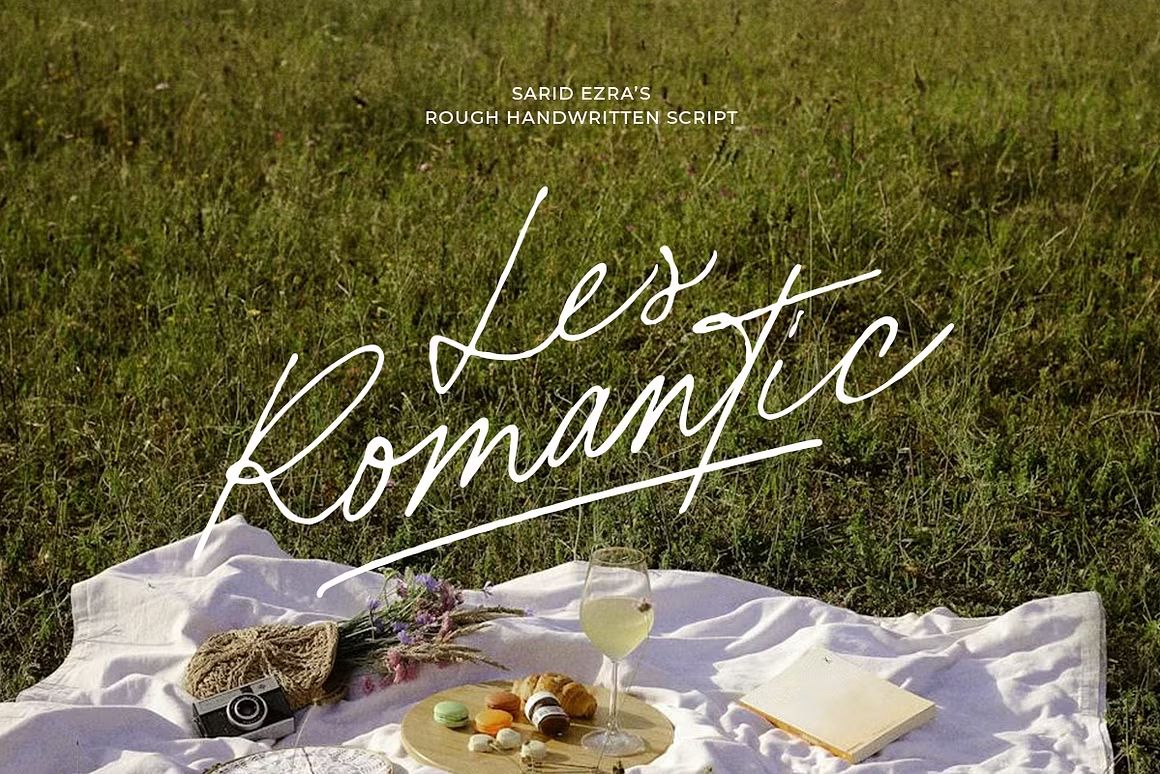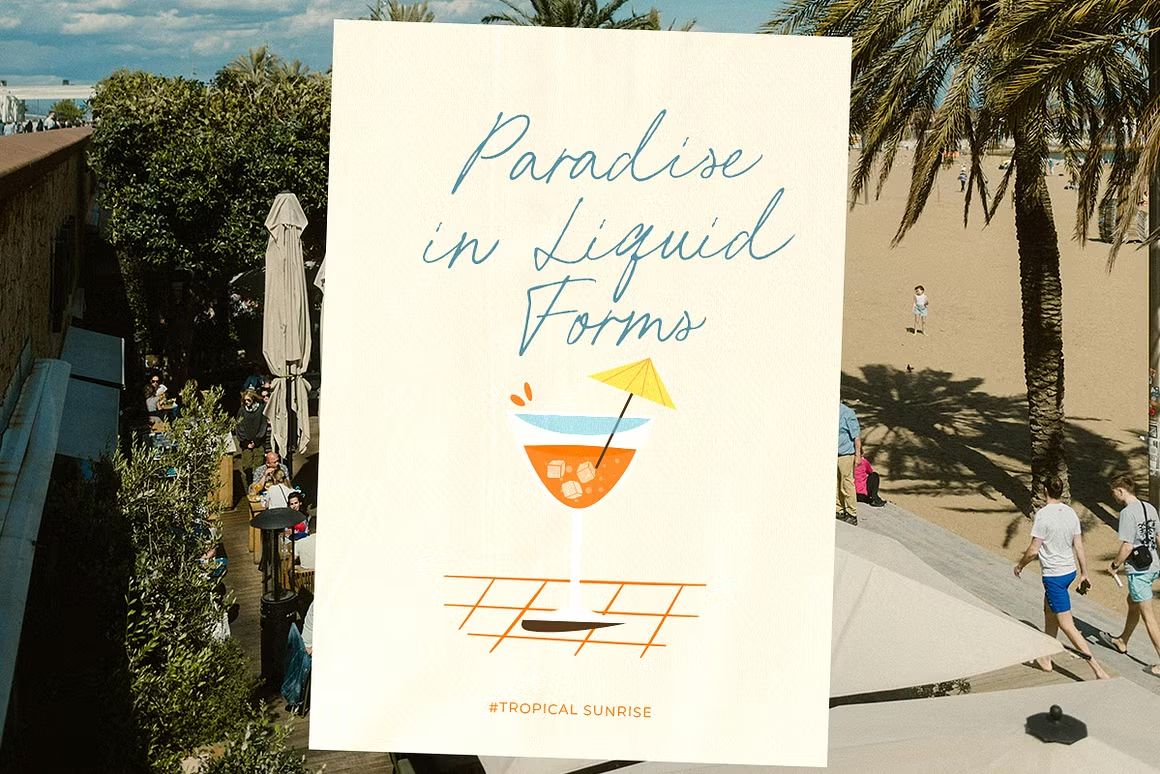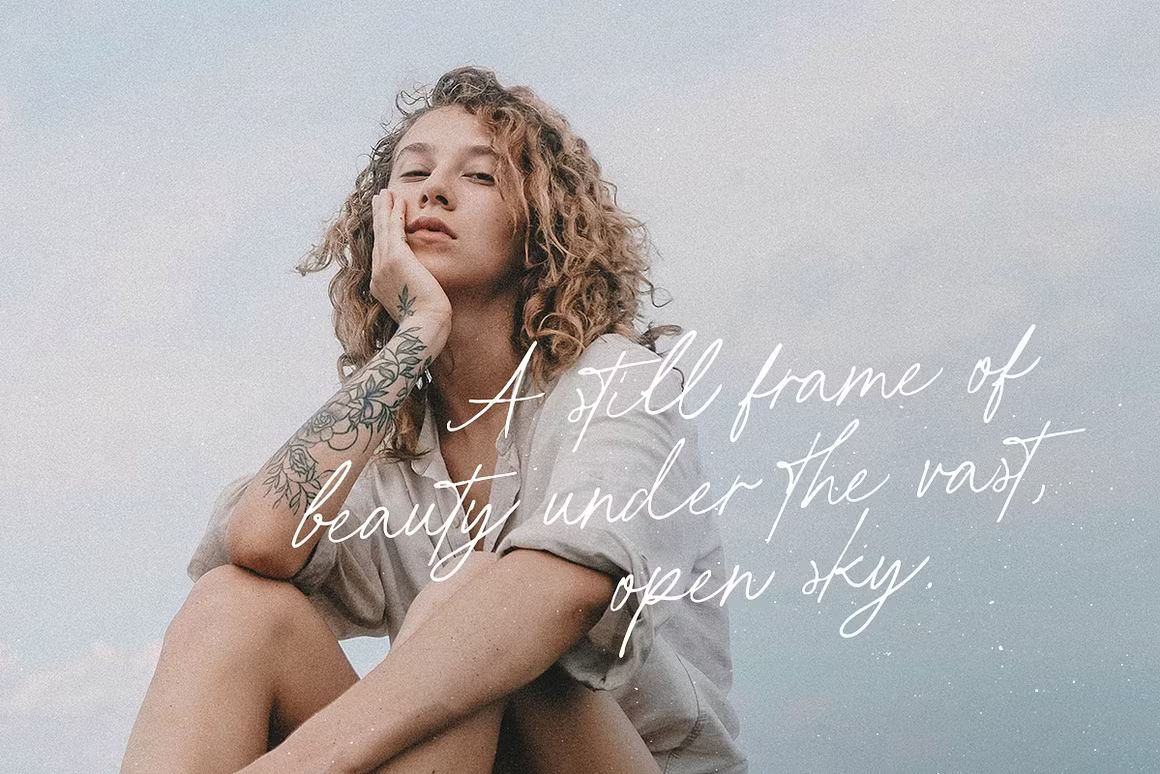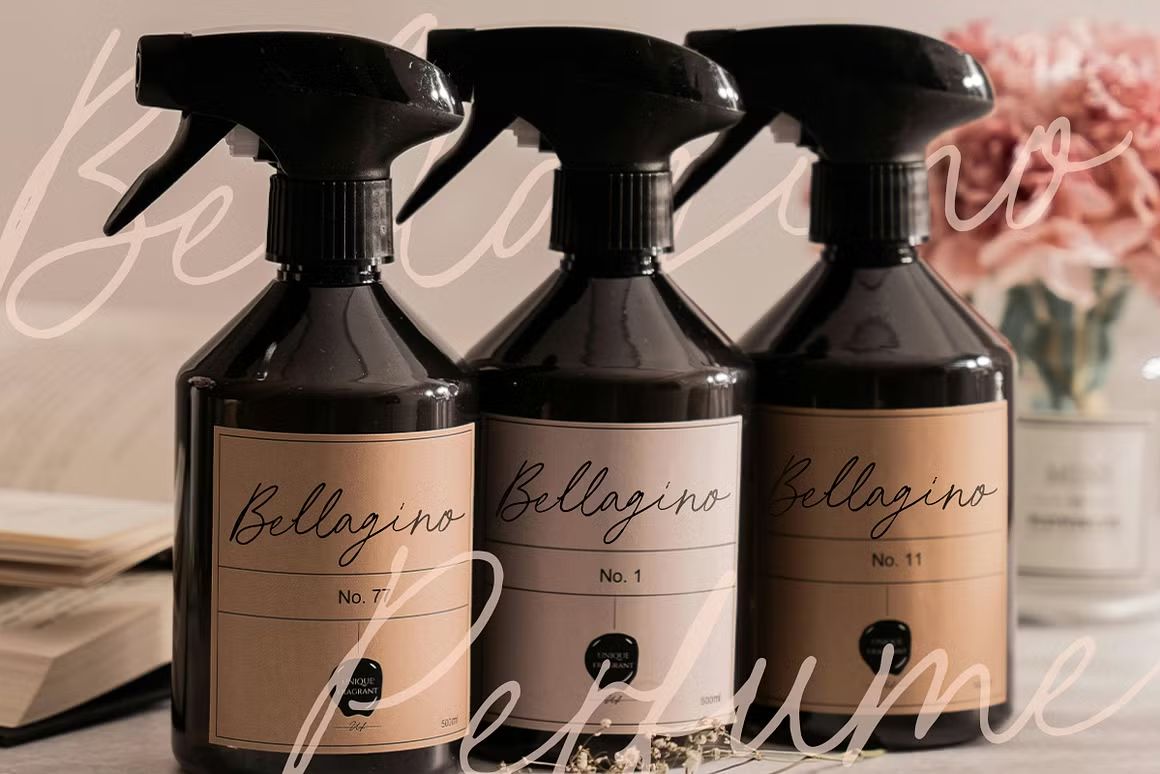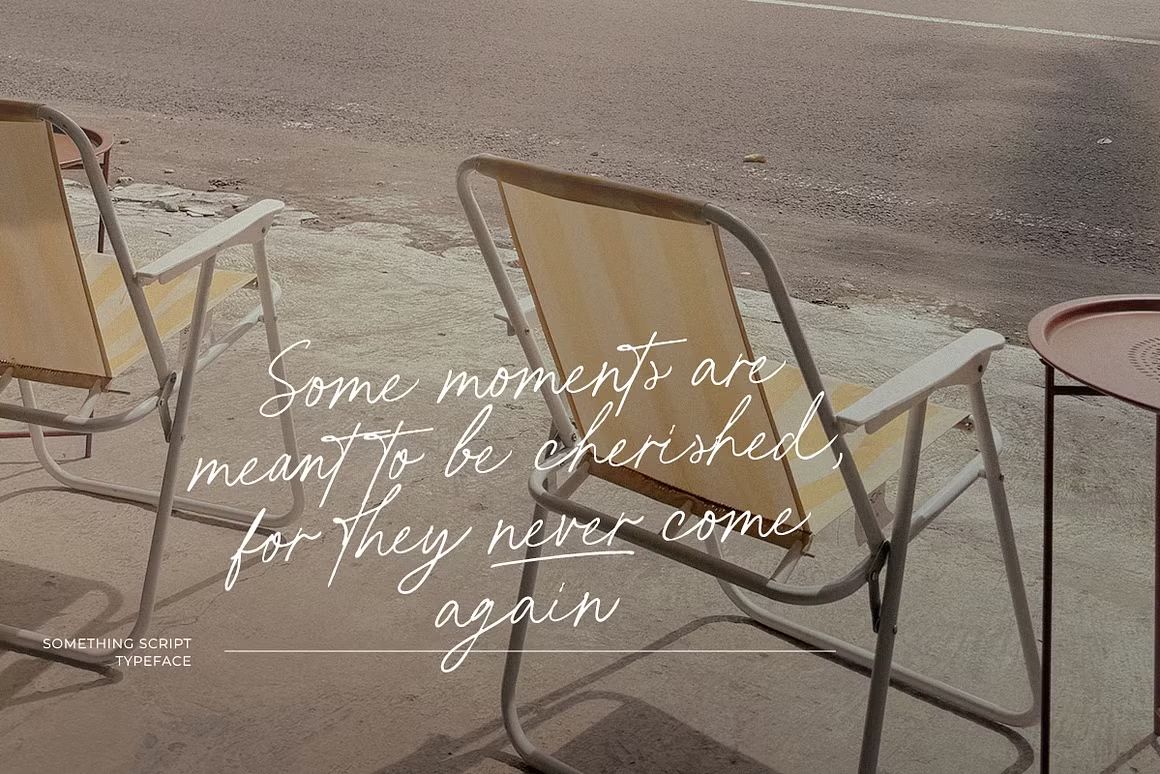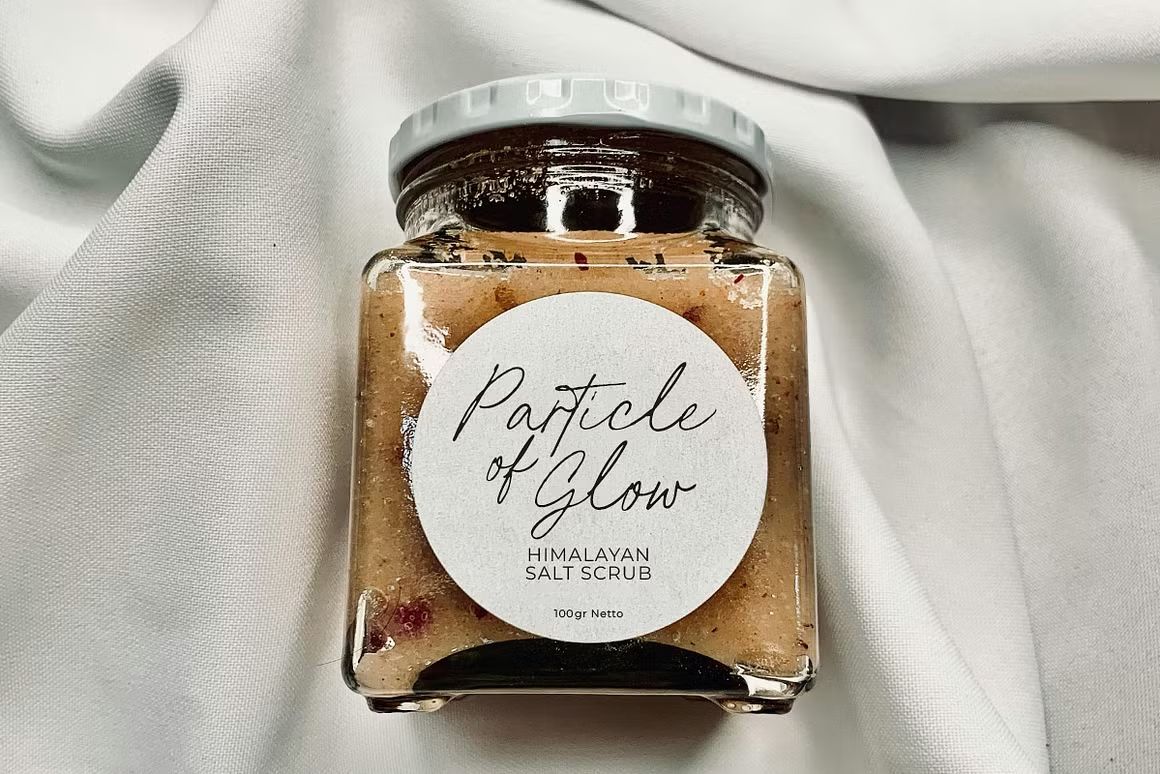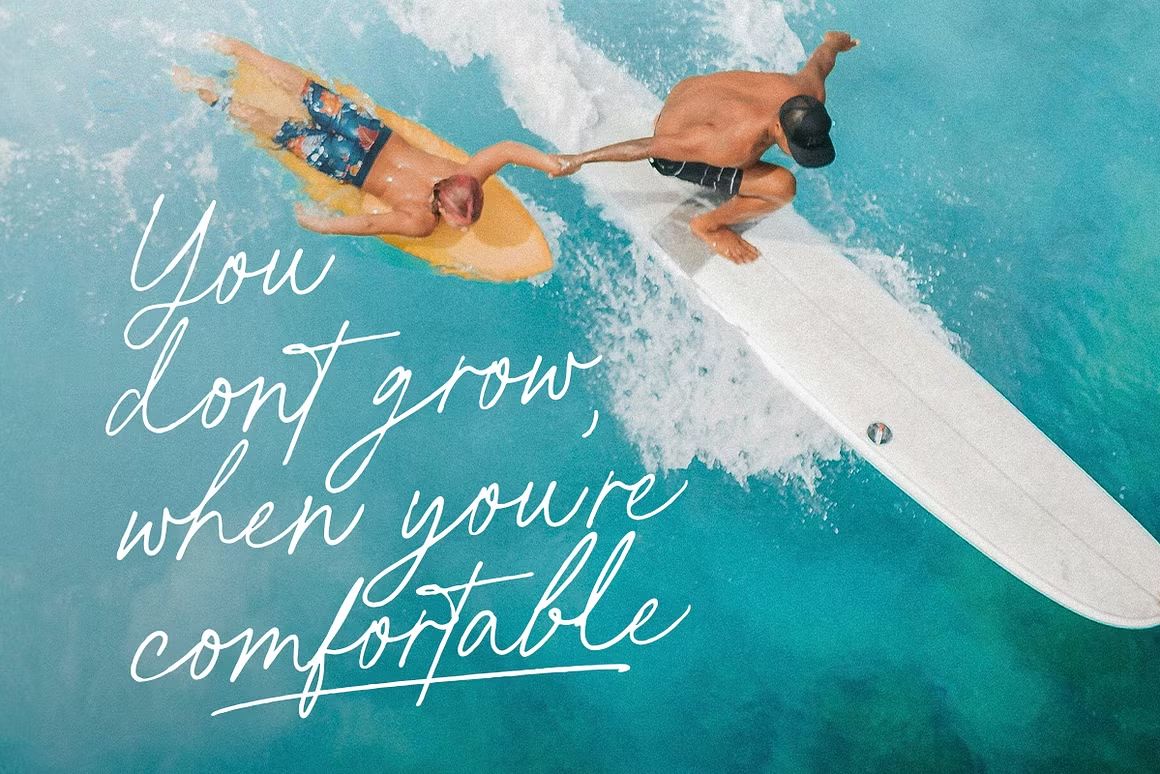
Les Romantic – Handwritten Font
Les Romantic adalah font handwritten dengan gaya elegan dan romantis, menampilkan goresan tangan yang lembut dan natural. Cocok untuk berbagai kebutuhan desain seperti undangan pernikahan, logo personal, kutipan estetik, kemasan produk, dan branding feminin. Font ini memberikan nuansa hangat, personal, dan penuh cinta dalam setiap elemen visual.
• Tulisan tangan bergaya romantis dan halus
• Ideal untuk wedding, branding, dan desain personal
• Termasuk huruf besar, kecil, angka, simbol, dan ligatur